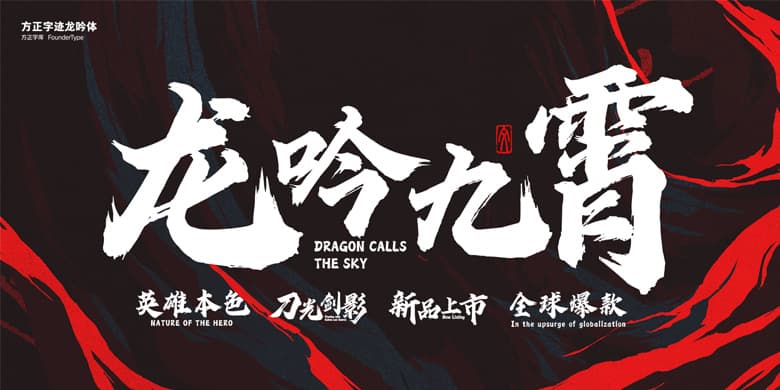
品牌:方正字迹设计师:曹基殿发行时间:2019字库编码:大陆简体(GB2312-80)、简繁扩展(GBK)分类:常规书写·毛笔字体属性:精品字
方正字迹-龙吟体笔画刚硬锐利,笔触狂放,字形浑厚洒脱,且结构多变。不仅适用于横向、纵向的排版,还方便了字与字之间的穿插。在继承传统的同时又融入当今商业化的应用,适合于电影海报、包装、品牌名称、各类商业海报、户外广告标题等。